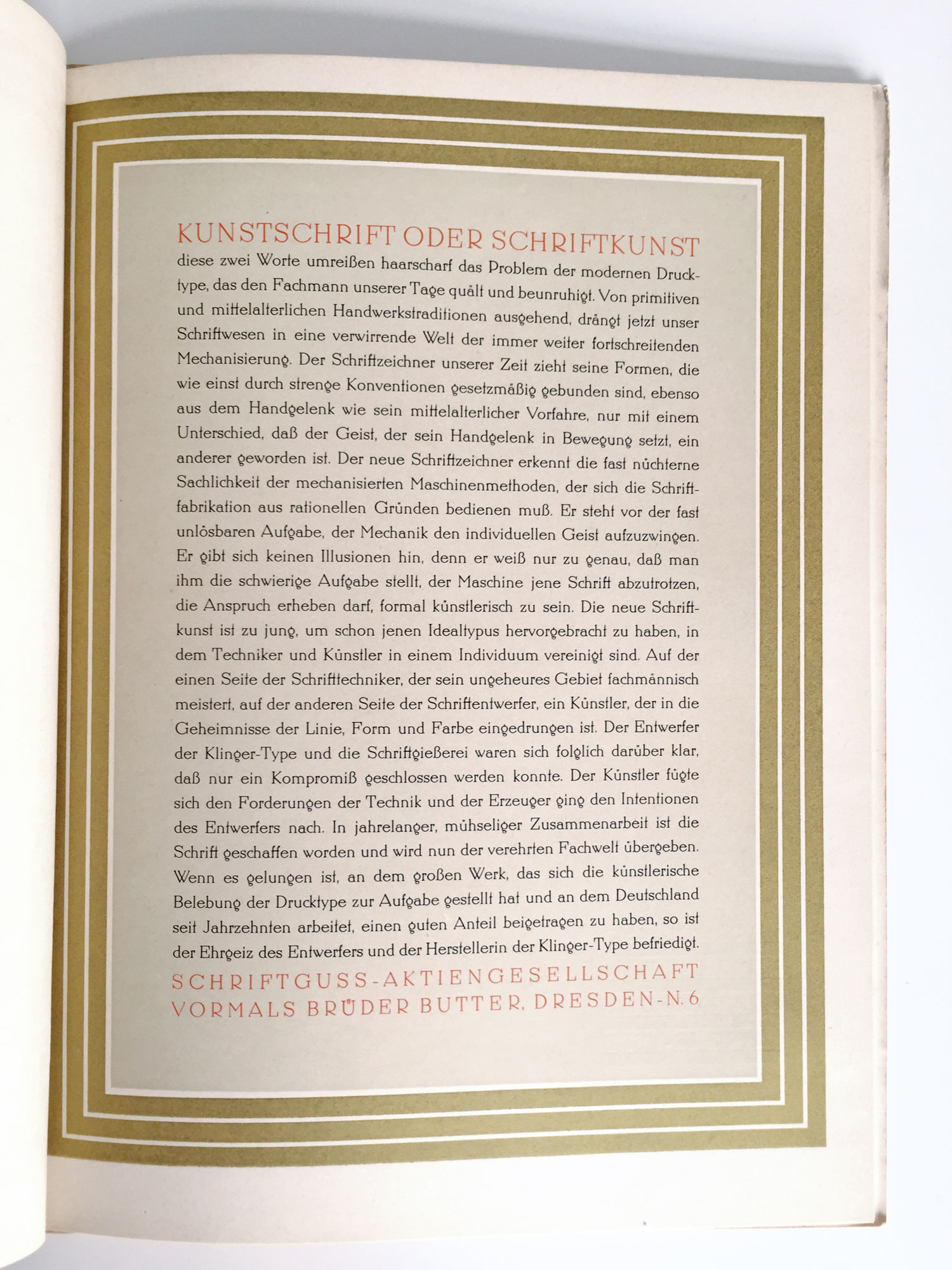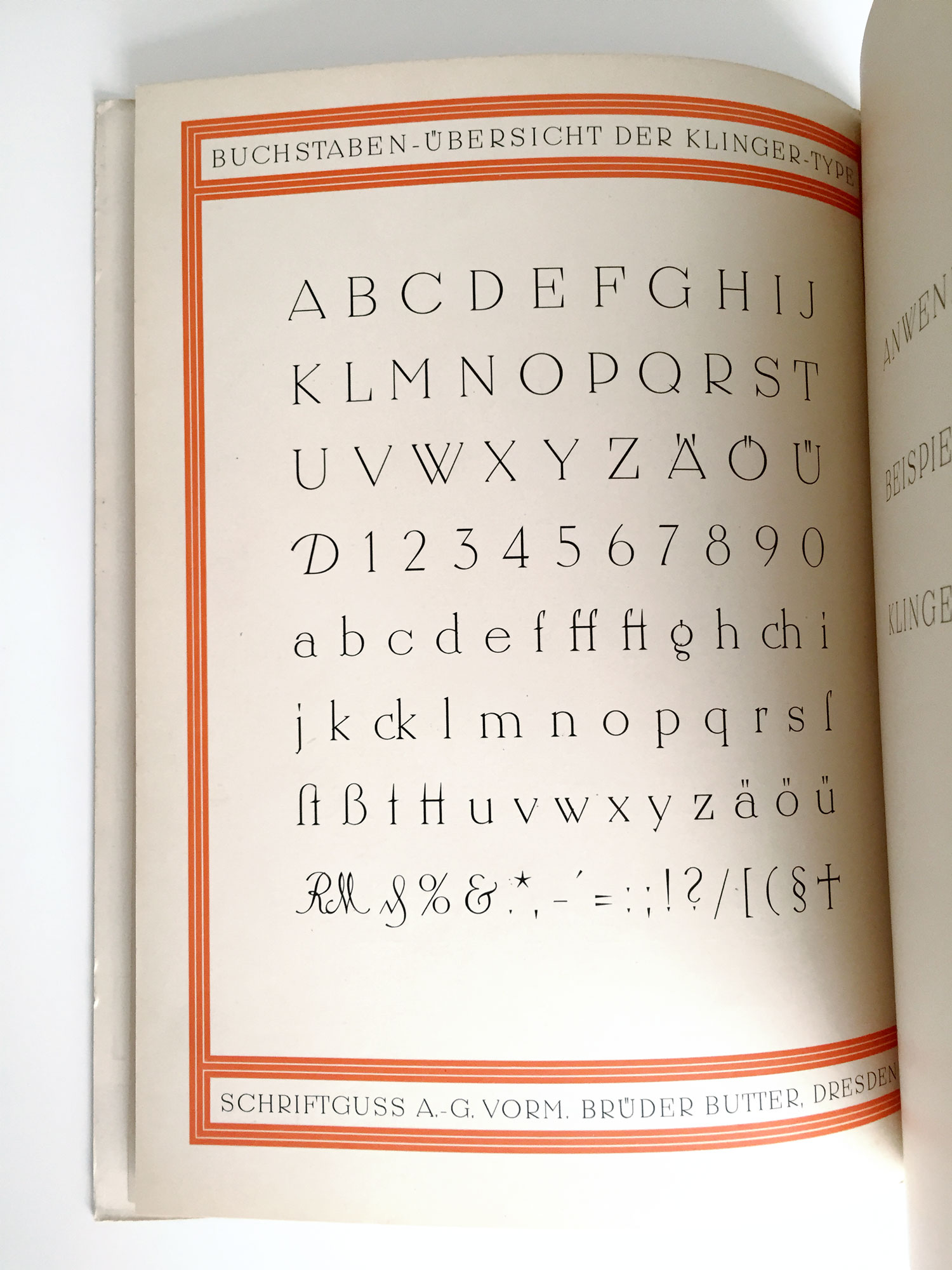
vintage design, nennt man sowas :hammer:
Das ist nicht Vintage, sondern Natural-Hipster.
Fette Times, Unterstreichung, kein Kerning, Fast-Überlappungen, Rahmen, Pastellfarben ... es fehlen nur Dreiecke / diagonale Kreuze.
Zwei Seiten aus einem Schriftmuster der Klinger-Type der Schriftguss AG von 1926. Der Introtext ist sehr amüsant und beim Buchstabenverzeichnis bin ich über das hübsche Ö gestolpert.
Aus der Kunsthalle Bielefeld: Ohne Titel (In the shade of absence) von Johannes Wald (2013).
Die Buchstaben wird in den Stein graviert, mit Blei ausgegossen und dann an der Wand aufgehängt. Der Text stammt vom Künstler selbst. Man sieht sogar die zunehmende Abnutzung der Vorlage im Verlauf des Textes – zumindest wenn man es in live betrachtet.
Die Versalien sind etwa zehn Zentimeter hoch.
Hier ist gerade die Examen-Korrekturphase ausgebrochen. Gerade gefunden: eine schöne studentische vv-Ligatur!
Dabei fällt mir ein: »in«, »im«, »it«, »if« und ähnliche Ligaturen sind in Fonts unüblich, oder? Ich stelle fest daß die die im Englischen dauernd benutze! Das sollte man vielleicht einmal hinzufügen! :huhu:
Sehr schön! So toll handschriftlich wirkende Fonts in letzter Zeit geworden sind (nicht zuletzt dank der Möglichkeiten von Opentype) sind viele wohl immer noch sehr »konstruiert« – und lassen viele Eigenarten tatsächlicher Handschriften unter den Tisch fallen. Aber mit immer weiter steigender Computerleistung und dem Antrieb für Schriftgestalter, neue Themen zu finden, wird sich da in Zukunft sicher noch einiges bewegen.
Hierzu passen m.E. die Kritzeleien in einem öffentlichen Baumhaus in Pennsylvania, die ich letzten Herbst fotografiert habe. Die Nachrichten an sich (meist im Format Joe & Susie Jahreszahl/forever) waren für Fremde belanglos – aber die Vielfalt der verwendeten Und-Zeichen hat es mir angetan:
Die ε̣̇-Form (auch mit durchgezogener Linie, analog zu $) ist die handschriftliche Standardform des &. Aber auch die »falsche« Alternativform mit nicht gespiegelter 3 sieht man recht häufig. Interessant auch die Form, die an ein Σ erinnert. Besonders spannend fand ich aber die einfachen Schlaufen, die eine Hybridform aus + und & darzustellen scheinen.
Die Frage, ob Kristins, Trevors und Kylees Beziehung in irgendeiner Weise asymmetrisch ist und der Autor dies durch die Wahl unterschiedlicher Und-Zeichen verdeutlichen wollte, muss wohl leider unbeantwortet bleiben.
Da ich schon immer mal wissen wollte, wie man mal polytonisches Griechisch auf einer Schreibmaschine tippt, und ich grad bei reddit mich durch ancientgreek lese, bekam ich doch glatt feuchte Augen, als ich dieses Schmuckstück hier sah: Eine alte Remington mit polytonischem Griechisch: http://imgur.com/MfIBV
Nach Sigmund Freuds Handschrift die neue Digitalisierung von Harald Geisler: Albert Einstein: http://www.sciencealert.com/you-ll-soon-be-able-to-type-everything-in-einstein-s-handwriting-thanks-to-this-new-font oder direkt Kickstarter: https://www.kickstarter.com/projects/1822548650/albert-einstein-font
Kein Schriftmuster sondern eine Ansammlung von "Fachmännischen Urtheilen" — über 24 Seiten mit Lobhudeleien, alphabetisch nach Orten von A wie Aachen bis Z wie Zwenkau sortiert. College Pachulke dürfte seine Freude daran haben. :party:
Ist schon lustig; andererseits auch wieder ziemlich peinlich, daß die ihren Kunden offensichtlich ein Rundschreiben mit der Bitte um solche Referenzen geschickt haben.
Ich kann mir allersings denken, dass die für Heißprägungen in Buchdeckeln das ideale Material sind, wirklich Prägefest und gut wärmeleitend.
Das braucht dann gar nicht den Lob-Orgien (auch wenn das, besonders im Internet noch heute gern gemacht wird, auch ohne dass es einers Rundschreibens bedarf. Oft schreibt man das einfach doch selbst!
Ist schon lustig; andererseits auch wieder ziemlich peinlich, daß die ihren Kunden offensichtlich ein Rundschreiben mit der Bitte um solche Referenzen geschickt haben.
dachte ich mir auch so, im grunde scheint das aber der vorgänger des i-like-buttons zu sein – oder? den binden ja die firmen auch auf ihrer website ein um kunden zu sagen "bitte like uns"
Ich hab’s zumindest noch nie gehört. Was machen denn andere Programme, wenn man diese Taste für den Apostroph verwendet – etwas anderes?
Diese »Smart-Quote«-Funktion gibt es bei unzähligen Textverarbeitungs- und Designprogrammen. Wenn man in freier Wildbahn dann diese Fehler findet, sind sie sicher eher selten von InDesign verursacht worden. Denn die Quote der Profi-Nutzer des Programms ist einfach tendenziell viel größer als bei Word, CorelDRAW und so weiter. Ich halte die Bezeichnung daher nicht für besonders angebracht.